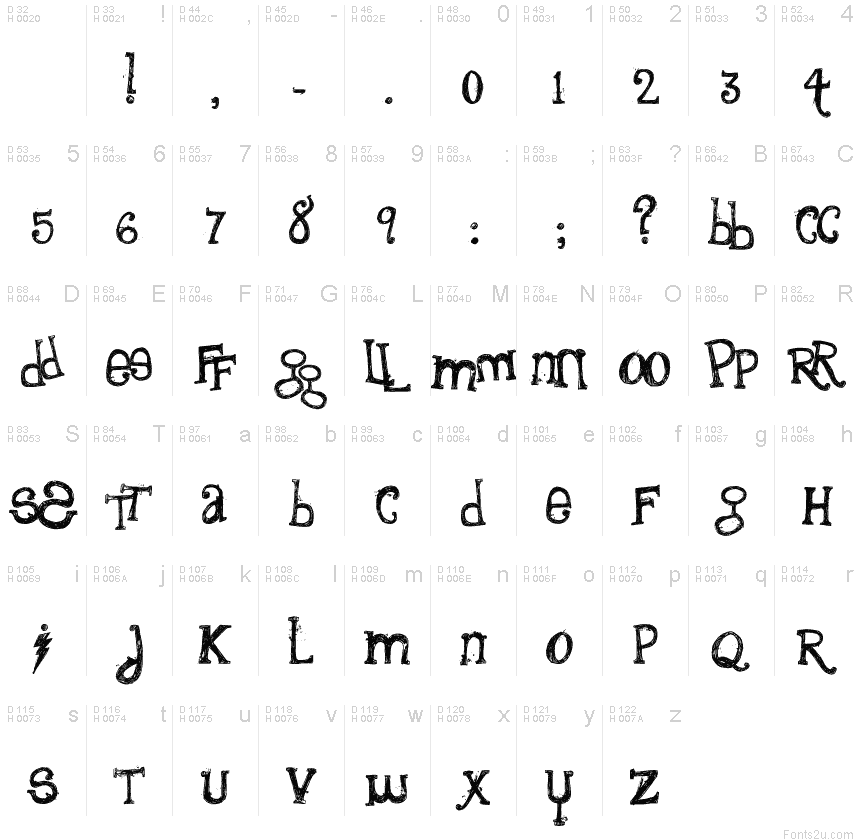
The Quiet Scream od Gyom-typo to darmowy, odręczny font o surowym, „podrapanym” wyglądzie. Litery sprawiają wrażenie chropowatych i nerwowych, z drżącymi konturami, poszarpanymi krawędziami i luźnym rytmem typowym dla mazaka, co nadaje im charakter rodem z zina, daleki od wygładzonej kaligrafii.
Idealnie sprawdzi się na plakatach, okładkach albumów, w tytułach filmów niezależnych, na okładkach książek czy nagłówkach ulotek, wszędzie tam, gdzie tekst ma brzmieć pilnie i być nieco zużyty. Jako darmowy font, świetnie nadaje się również do krótkich haseł reklamowych czy wyróżnionych cytatów, ponieważ nieregularna tekstura nadaje nawet kilku słowom klimat nocnej notatki pisanej na szybko.